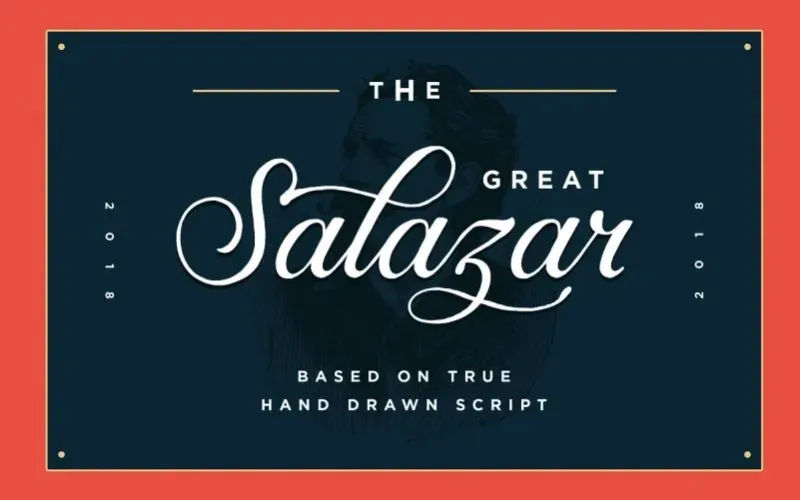
A Salazar Font é uma elegante tipografia script criada pelo Studio Konstantine, ideal para aqueles que buscam um efeito único em suas criações. Com traços leves, característica de corte condensado e personalidade divertida com um toque de ligaduras, esta fonte foi cuidadosamente construída para manter o charme clássico que faz do Salazar Script uma escolha popular entre designers. Suas linhas suaves e seu estilo reconfortante prometem dar ao seu design um brilho único e atraente, tornando-a uma opção ideal tanto para aplicações comerciais quanto pessoais. Com a Salazar Font na sua paleta de recursos gráficos, você poderá explorar novos níveis de expressividade e personalização no seu trabalho.